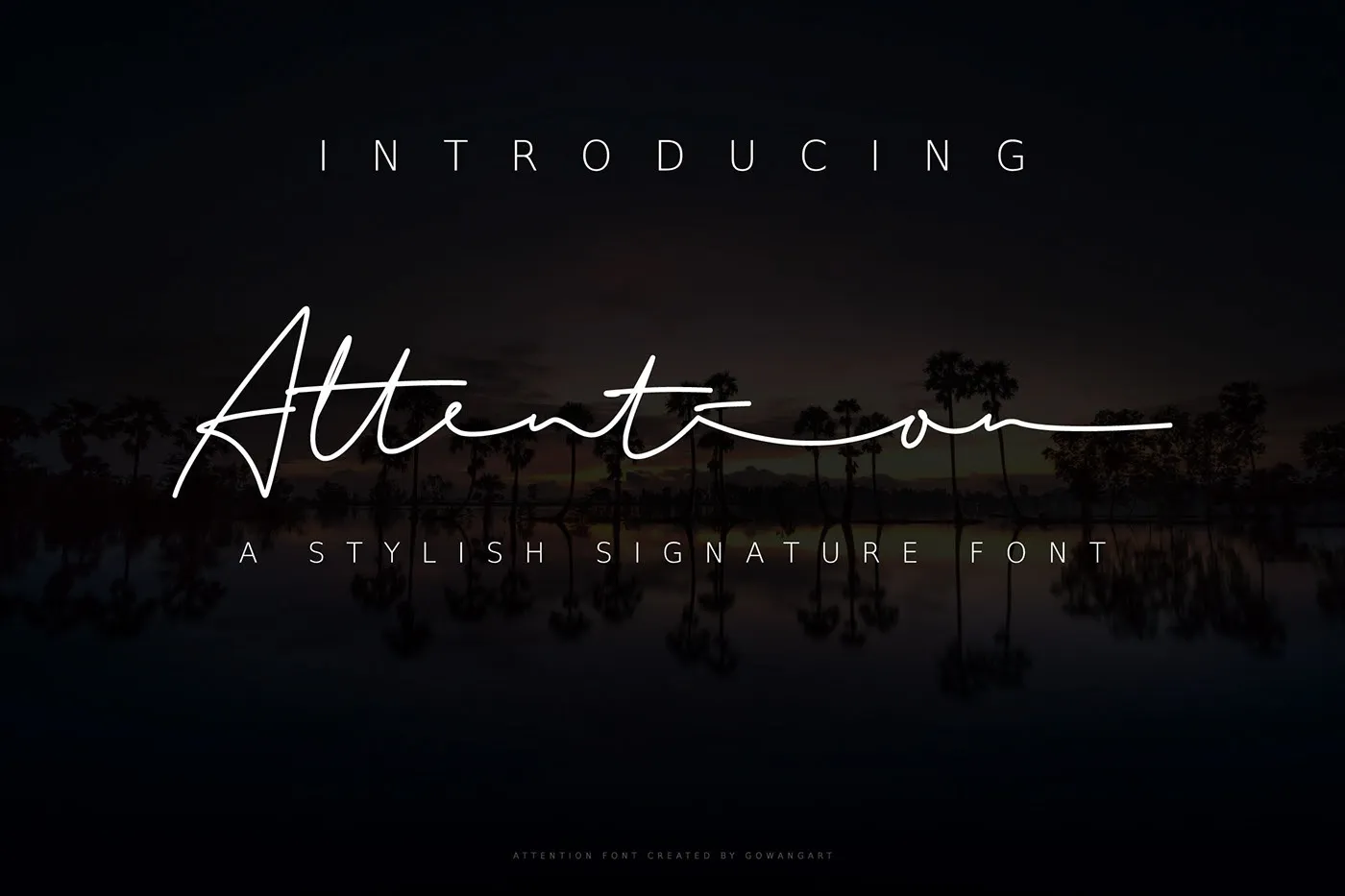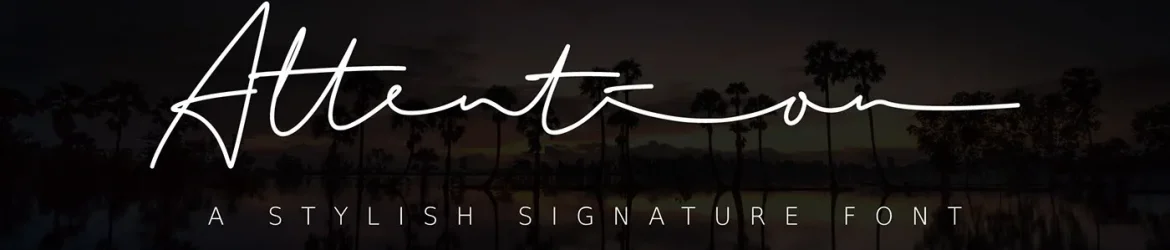
Attention Font – Download Grátis
Esta fonte escrita a mão, com traços monolíneos criada por PS Ari Setiawan, é perfeita para aqueles que buscam algo romântico e delicado. As letras dançam ao longo do nível da linha base, exibindo um toque casual e elegante. A fonte é ideal para assinaturas, marcas de marca, etiquetas, postais, roupas, citações e muito mais. Seu estilo inconfundível e a sua sensibilidade criativa tornam-a uma escolha única e memorável. Não importa do campo que você esteja trabalhando – seja ele moda, design editorial ou arte digital, esta fonte oferece um toque especial para seu projeto. Seja de uma maneira romântica e delicada, ou de uma maneira elegante e sofisticada, essa fonte é o seu próximo favorito. Experimente-a hoje!